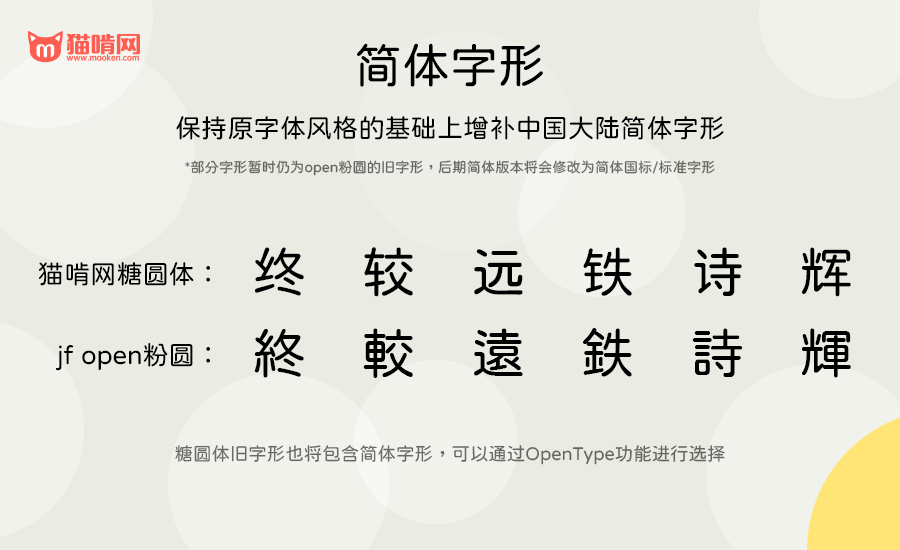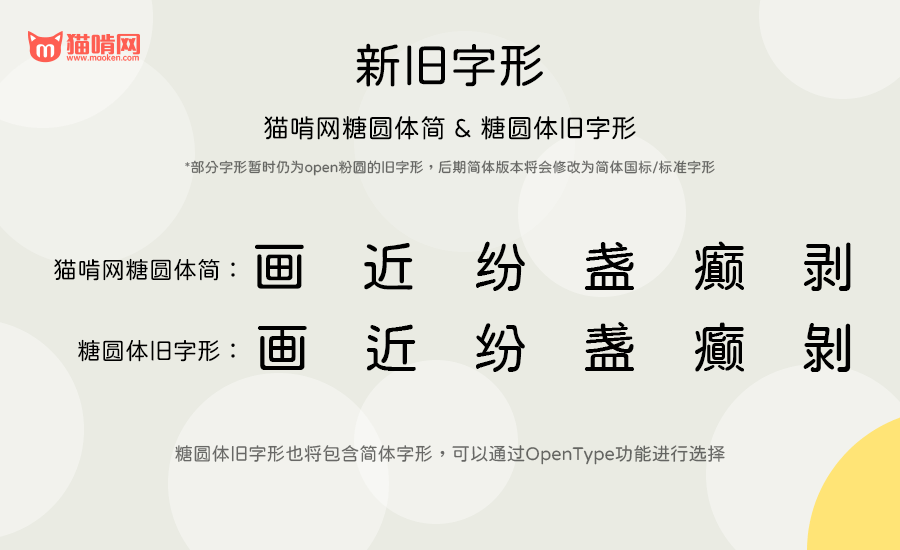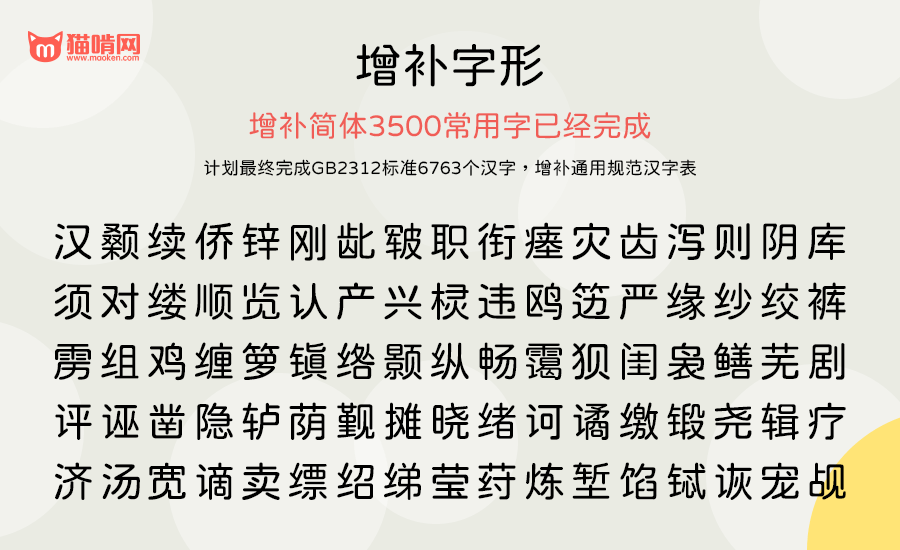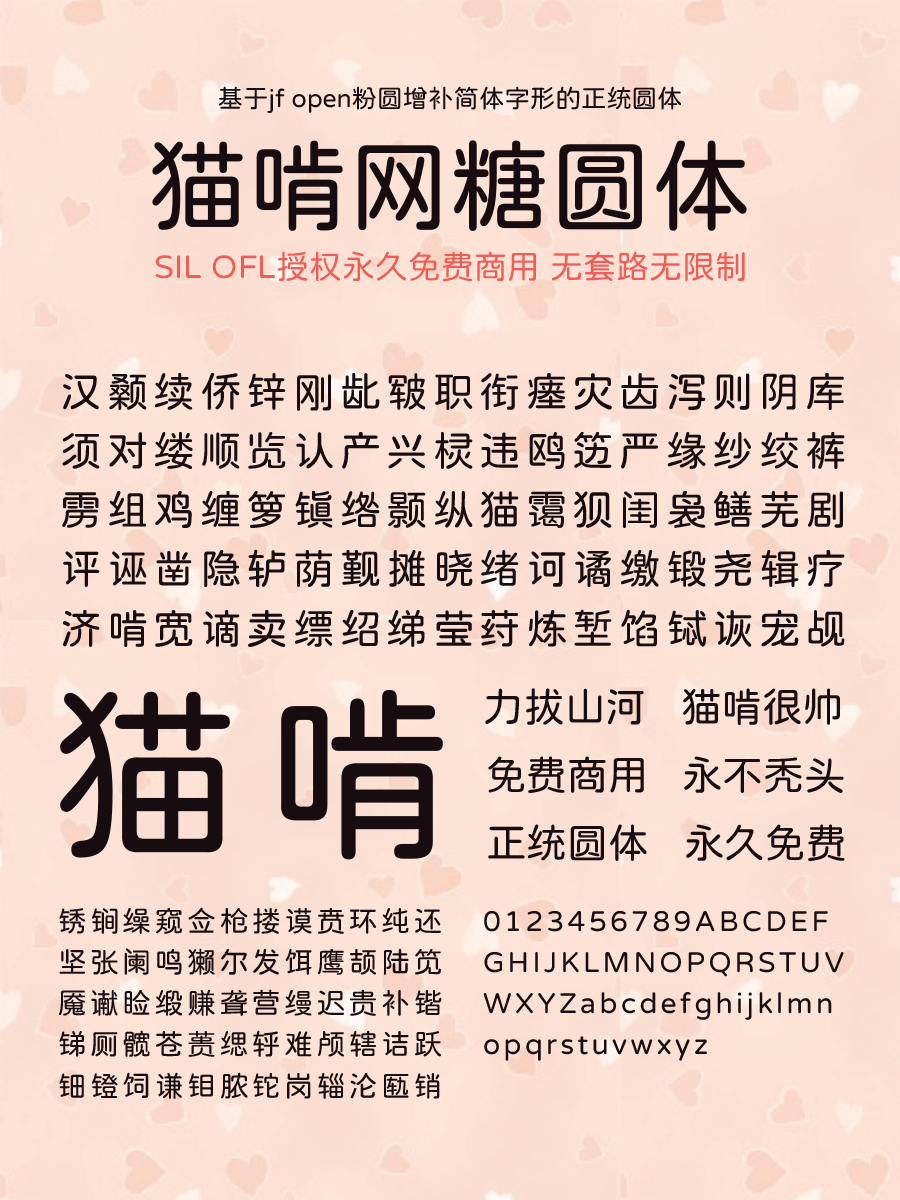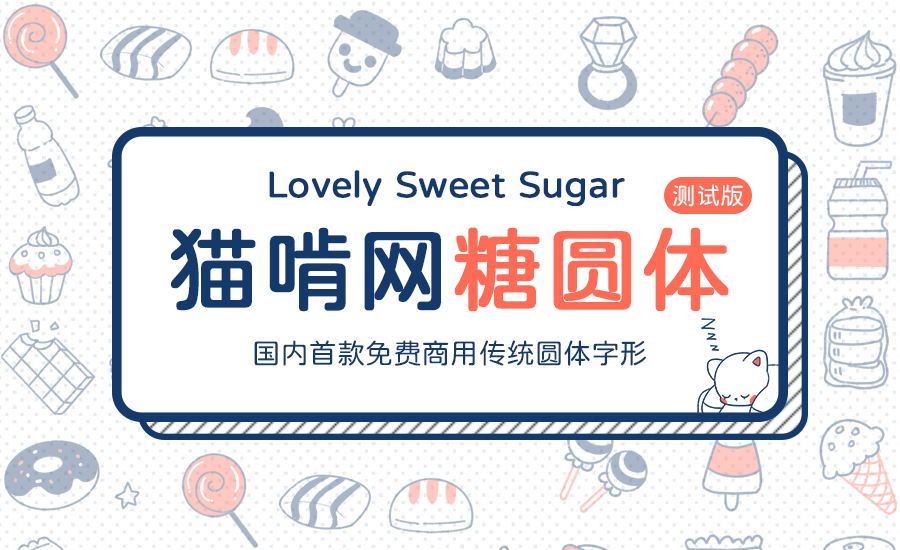
猫啃网糖圆体:基于jf open粉圆增补 国内首款免费商用传统圆体字形字体资讯
猫啃网自从上线之后,搜集了国内外近200多款免费商用的中文字体,但是一直感慨的是还没有一款免费商用的圆体字库。现在的圆体字库,很多都是基本于思源黑体通过程序进行改造,把笔画变圆,但是看上去还是很有黑体的感觉。
后来台湾的justfont发布了一款以“小杉圆体”进行修改增补而成的圆体字形“jf open粉圆”,十分受欢迎。但是可惜的是,这款字体以繁体为主,对大陆的小伙伴来说要用起来就十分尴尬,因为简体缺字太多。有感于此,猫啃君开始了“jf open粉圆”的简体增补计划,希望可以基于粉圆字形补全简体字形以方便大陆的小伙伴能愉快地使用该字体。
目前“猫啃网糖圆体”已完成简体3500常用汉字的增补,未来计划最终完成GB2312标准6763个汉字,增补通用规范汉字表。再加上原有的粉圆简体部分的字体和@猫啃君和@夜煞之乐增加的简体字符,实际上猫啃网糖圆体已经包含简体字5671个,已经能满足大部分的简体字需求。但是后续@猫啃君会继续努力,把剩下的字体继续补完。
目前“猫啃网糖圆体”在保持原字体风格的基础上增补大陆简体字形。
糖圆体将会分为两个版本,一个是“猫啃网糖圆体”,这个版本将会以简体字体为主,在写法上会更贴近中国大陆的简体的习惯写法,现阶段准备发布的测试版本字体中许多字仍是旧字形,这些字将在完成gb2312的汉字后才会一并进行修改。
而另一个版本是”糖圆体旧字形“,这个版本主要由@夜煞之乐进行维护。旧字形版本将会包含简体和繁体的字符集,在字形上以贴近原open粉圆的旧字形为主。另外,该字体也会通过opentype功能提供简体版本的字形进行选择,但是在不支援opentype的软件中仍会显示旧字形。
现在猫啃网糖圆体已完成3500个常用汉字,能满足一般的设计需求。再加原有的粉圆简体部分的字体和@猫啃君和@夜煞之乐增加的简体字符,实际上猫啃网糖圆体已经包含简体字5671个,已经能满足大部分的简体字需求。但是后续@猫啃君会继续努力,把剩下的字体继续补完。